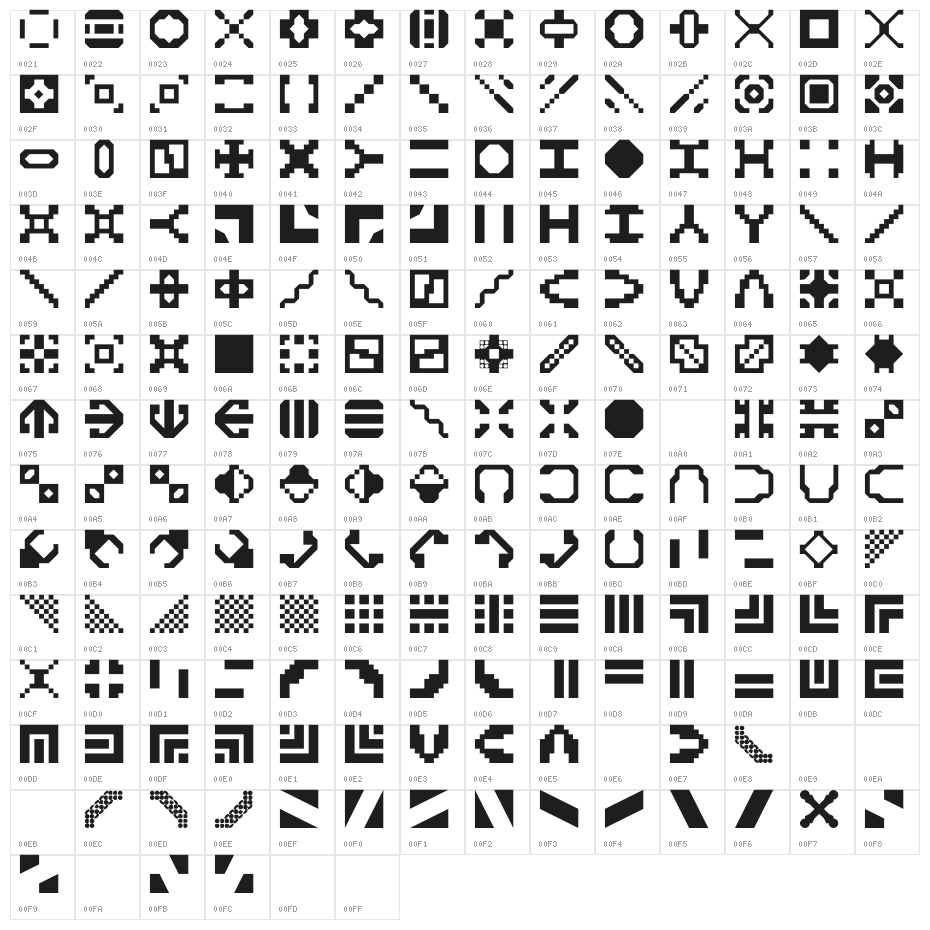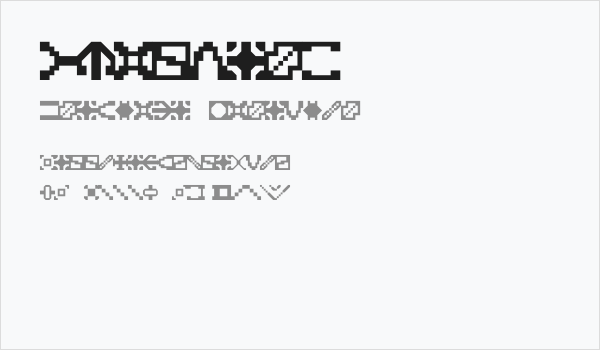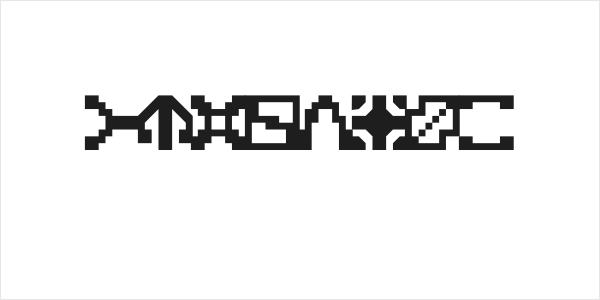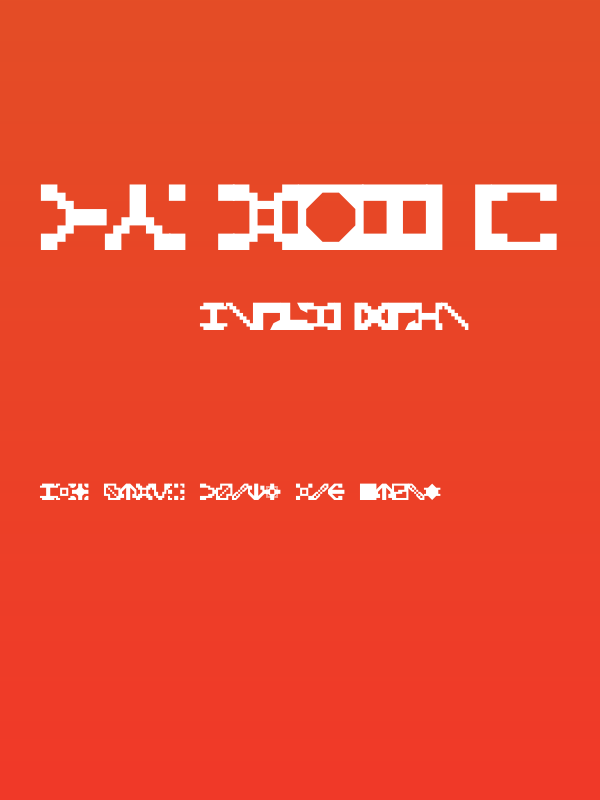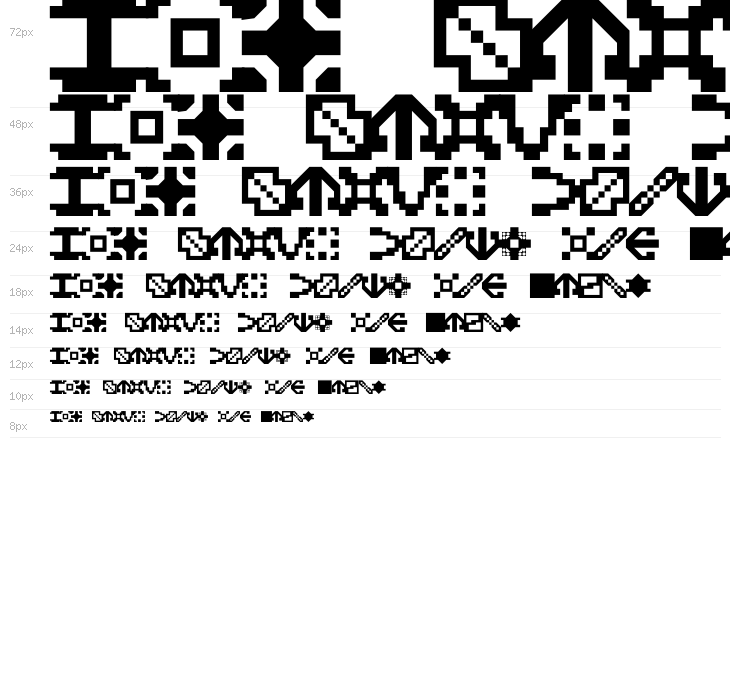
Builder2 Font
| Gesamtstil | Abstract, Geometric |
| Anwendungsfall | Decorative elements, Art projects |
| Vorgeschlagene Projekte | This design could be used for decorative purposes, such as in graphic design projects, artwork, or as a pattern for textiles. |